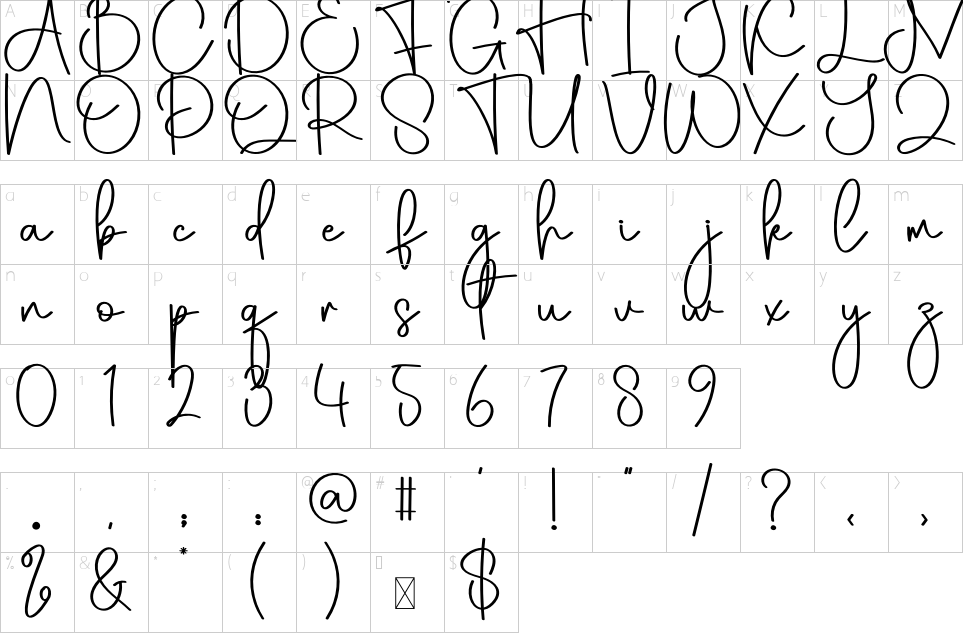
A fonte ‘Prewedding Font | 1001 Free Fonts’ é uma opção prática para aqueles procurando por um design elegante e minimalista para seu álbum de fotos de casamento. Desenvolvida por scratchones, esta fonte pode ser facilmente instalada tanto em sistemas Windows quanto em Mac, tornando-a uma escolha versátil para quem quer adicionar um toque especial a seus documentos de pre-wedding. Com seus designers habilidosos criando fontes únicas e versáteis, a fonte ‘Prewedding Font | 1001 Free Fonts’ oferece uma variedade de opções para quem está buscando um visual moderno para seus trabalhos. Recomendada para designers e amantes de gráficos, este é um dos muitos recursos gratuitos disponíveis na plataforma, garantindo que os designers possam acessar uma ampla gama de opções sem se preocupar com custos adicionais.